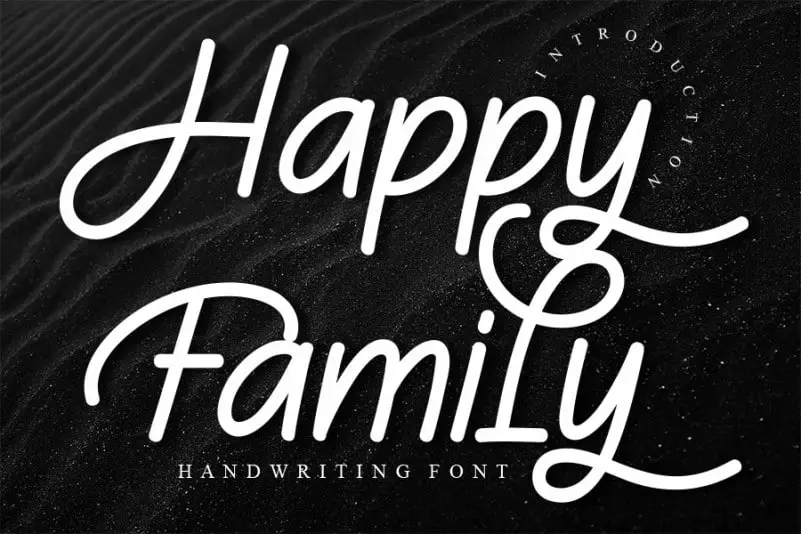
Happy Family Script Font – Download Grátis
A Happy Family Script Font é uma nova adição à coleção de letras escritas a mão, criada pelo Designer CreativeLetter. Embora seja uma fonte curvilínea e suave, ela carrega consigo um toque único que pode transformar qualquer texto em algo especial. Ideal para quem busca expressar amor, carinho e unidade familiar através da tipografia, esta fonte traz consigo uma sensação encantadora. Ela é perfeita para criações como cartões de aniversário, calendários ou até mesmo rascunhos para lembranças pessoais. Sem dúvida alguma, a Happy Family Script Font oferece ao seu design um toque especial e personalizado que não deixará ninguém indiferente. Seja você que quer escrever uma carta apaixonada ou simplesmente criar algo belo para compartilhar em sua vida, esta fonte é certamente o item ideal para incorporar a sensação da família em suas criações digitais.